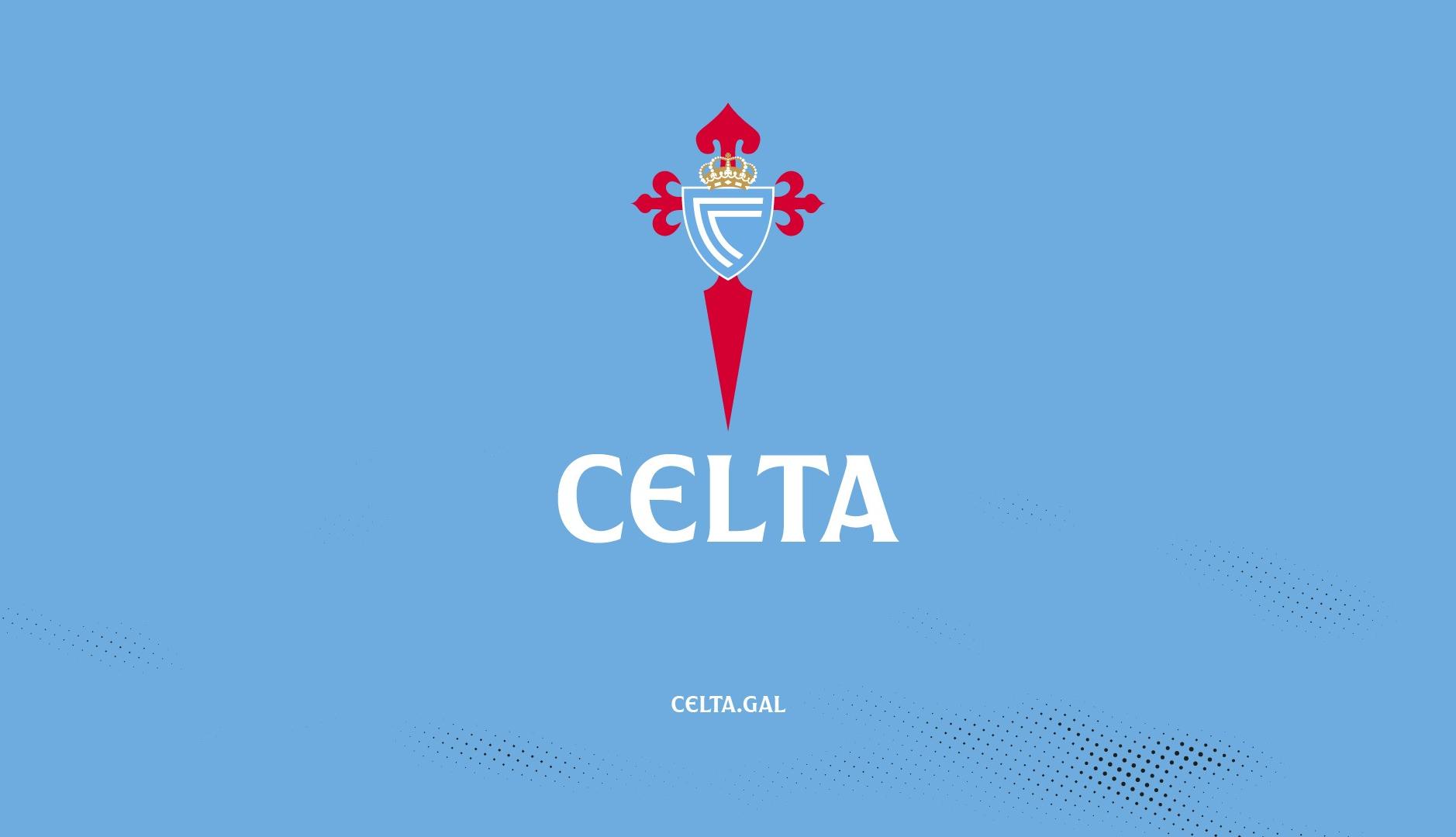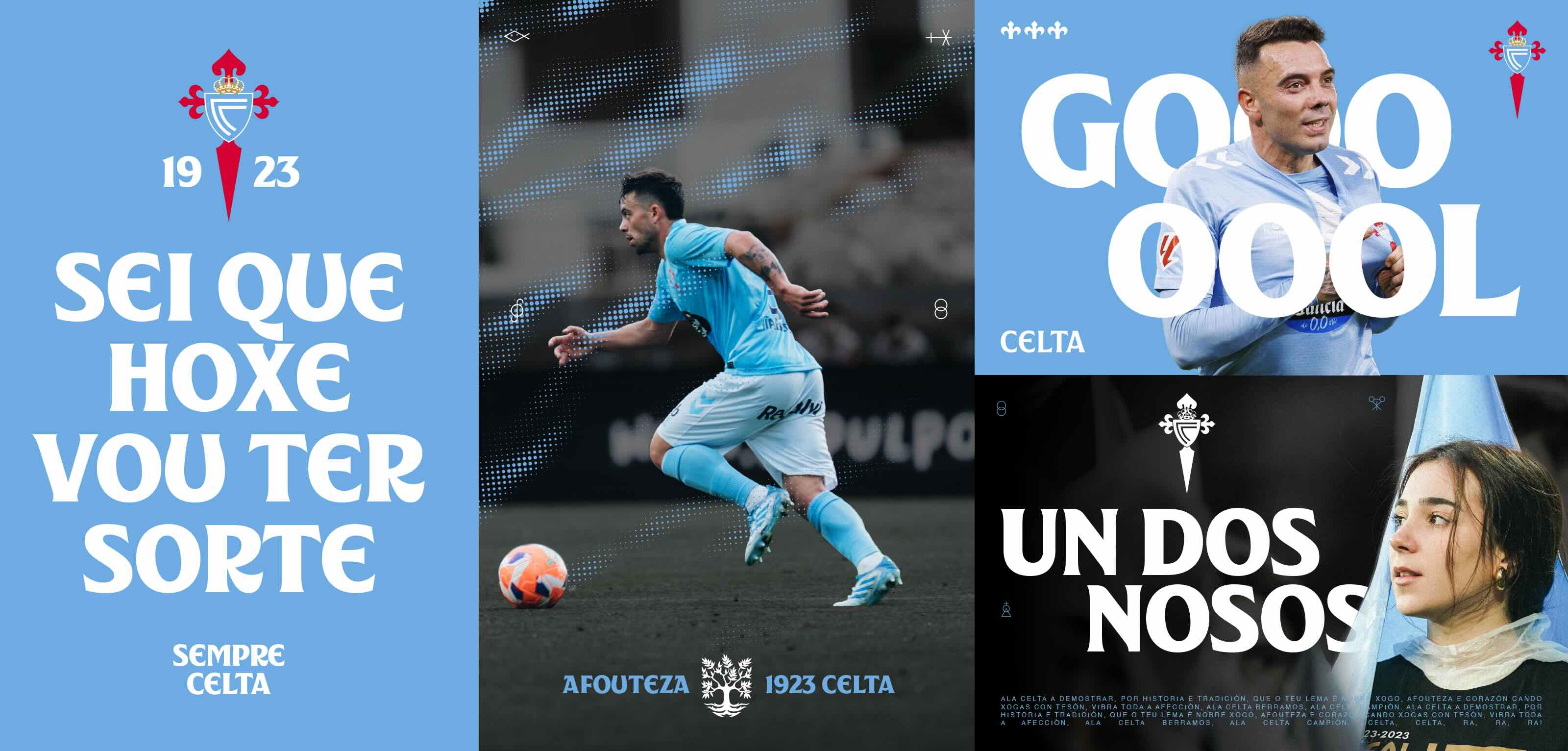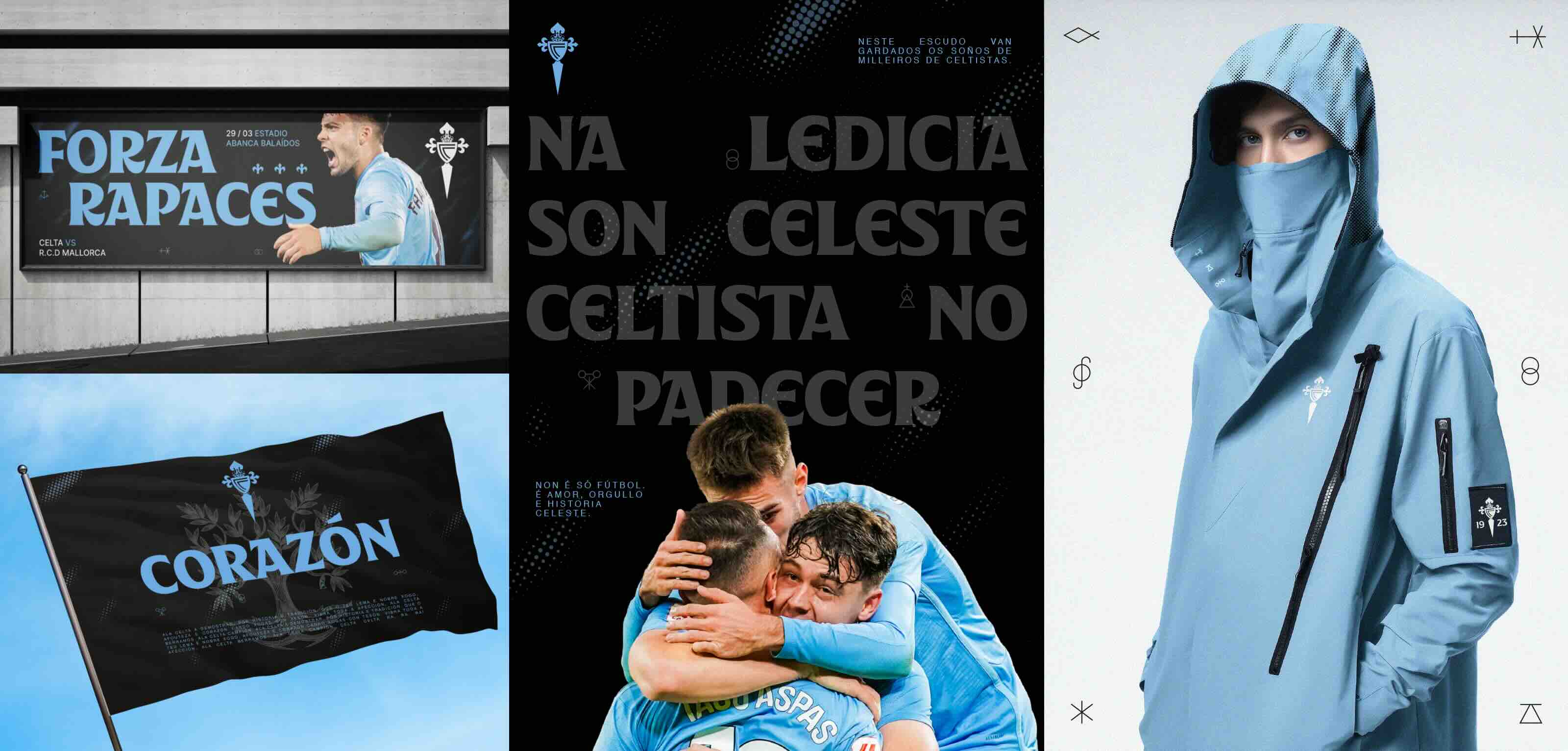
El Celta de Vigo actualiza su marca: nueva denominación y tipografía y más orígenes gallegos
• Refuerza su personalidad estrechando el vínculo con Galicia y su cultura
• La renovación se ha realizado junto a la consultora de branding Summa
Logotipo Celta
El club Celta de Vigo ha llevado a cabo una actualización de su marca, una con la que refuerza y amplía sus orígenes e identidad gallegos. La renovación incluye una nueva denominación para la entidad, una nueva tipografía y un nuevo dominio para su sitio web que estrecha aún más su vínculo con la región.
El trabajo se ha realizado en colaboración con la consultora de branding Summa, y ha buscado un impulso estratégico a la personalidad del club gallego. En este sentido, tal y como ha señalado la propia marca, a partir de ahora el equipo pasará a presentarse como Celta en todos los espacios vinculados a la comunicación. La denominación convivirá con las habituales hasta el momento, es decir, Real Club Celta, Celta de Vigo o RC Celta.
“Este cambio responde a una realidad evidente: para aficionados y aficionadas, para el fútbol en general, siempre fuimos simplemente el Celta”, ha expresado el club en un comunicado. “Reconocernos así es reconocer nuestra forma de sentir y de expresarnos, más próxima, más auténtica”.
En lo que respecta a la identidad, permanece intacto el escudo al que, según señala el club, sólo se le han aplicado ajustes técnicos en el diseño. También e mantiene una estética que apuesta firmemente por la identificación con el color celeste, que protagoniza una paleta que además cuenta con el blanco, el rojo, el dorado y el negro, que según la agencia, aporta profundidad, contundencia y una conexión con la dimensión industrial de la ciudad.
A este respecto, el principal cambio en la identidad visual del Celta es la tipografía, que se ha desarrollado junto al diseñador Pedro Arilla, de Arillatype Studio. Denominada “Siempre Celta”, ha sido ideada específicamente para el club gallego y está inspirada en el arte, el territorio y la tradición gallega. “Le da voz visual a nuestra personalidad: orgullosa, valiente y con carácter propio”, señala el club.
La identidad también incluiye texturas que evocan el entorno y la vida viguesa, como la niebla atlántica, la lluvia persistente, el mar  o las chispas de los astilleros. También se han incorporado símbolos abstractos inspirados en las antiguas marcas gremiales, presentes en construcciones históricas de toda la región, con la intención de conectar pasado y futuro desde lo simbólico.
La agencia Summa asegura que la estrategia va más allá de un cambio visual; y supone una vuelta al origen y la voluntad de representar a todos los gallegos y las gallegas. Así, el trabajo ha incluido una redefinición del manifiesto, con la afouteza (valentía) y el Celtismo en el centro; así como una revisión de los valores y la arquitectura de marca con la intención de dotar al club de un relato sólido que inspire dentro y fuera del campo.
“El reto no era solo diseñar una nueva identidad, sino capturar y amplificar el alma del Celta. Hemos creado un universo visual y verbal que honra sus raíces, conecta con su gente y proyecta con ambición su futuro". ha señalado Joan Mendoza, New Business Manager de Summa Branding, en un comunicado. "Un gesto de orgullo colectivo, una afirmación cultural y un impulso renovado para seguir escribiendo, con coraje y belleza, la historia del Celta”.
Además, como parte del proceso de renovación, el club ha adoptado un nuevo dominio web principal: celta.gal. Así, a lo largo de las próximas semanas, todas las plataformas digitales irán migrando del actual rccelta.es a celta.gal, en lo que el club considera que es una consolidación de la apuesta del Celta por su tierra natal y por poner en valor a lengua, la cultura y la identidad de la región. Eleva así su ambición y proyección por ser no sólo el club de Vigo, sino el club de Galicia.
“Esta evolución es una reafirmación de nuestra identidad. Más que una nueva marca, es una manera de decir quién somos, de donde venimos y cara donde vamos”; explican desde el club. “La marca Celta se actualiza reforzando su personalidad y raíces para proyectar, con aún más fuerza, la nuestra”.